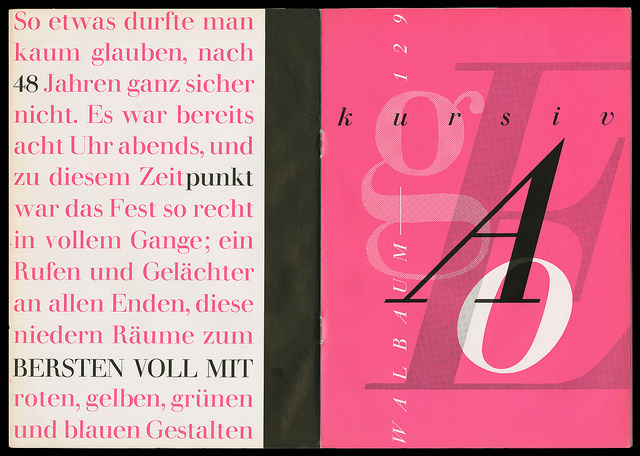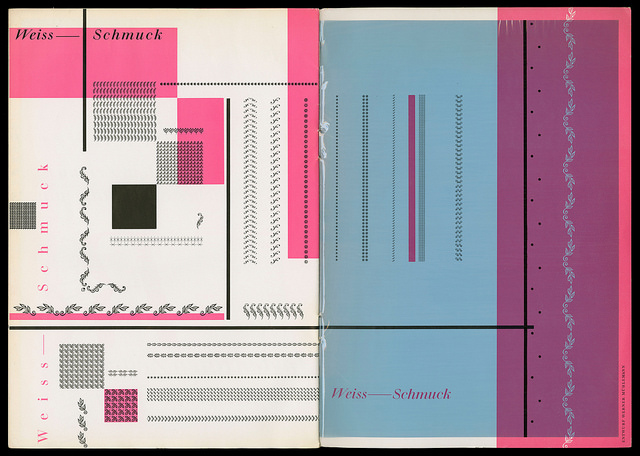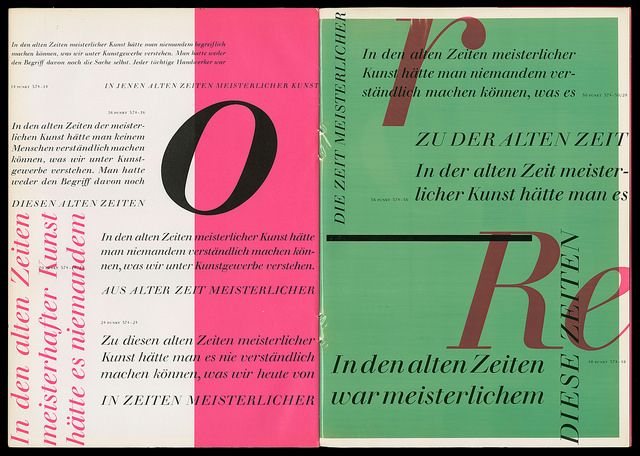
Schriftmuster MT Walbaum (1957)
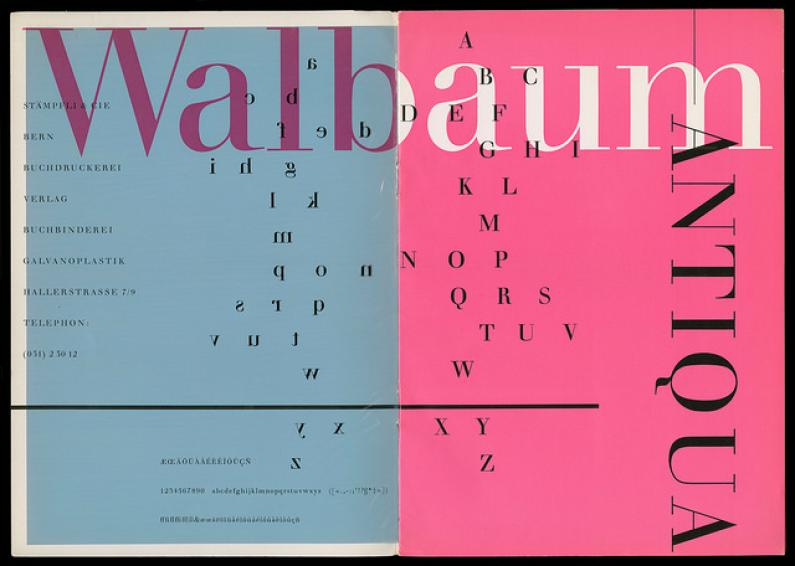
Doppelseiten aus dem Schriftmuster «Walbaum-Antiqua / Weiss-Schmuck» der Berner Buchdruckerei Stämpfli & Cie aus dem Jahr 1957. Aufwändig gestaltet (u. a. unter Einsatz bedruckter, farbiger Cellophanfolie) von Werner Mühlemann (1917–2012), dem damaligen Hausgrafiker der Druckerei. Mühlemann schuf für verschiedene Verkehrsvereine im Kanton Berner des Weiteren eine Reihe von Tourismusplakaten und war in den 1950er Jahren verantwortlich für die Gestaltung der Jahresberichte des Schweizer Skiverbands SSV.